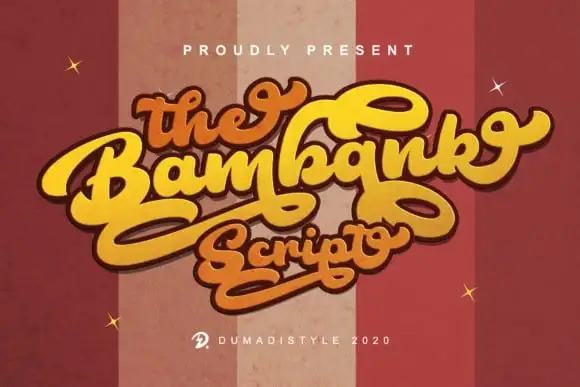
The Bambank Script Font – Download Grátis
A fonte ‘The Bambank Script Font’ é uma nova criação cuidadosamente meticulosa que adiciona linhas suaves e balanceadas a uma tipografia de script com personalidade. Suas letras fluídas são perfeitas para criar mensagens atrativas. Esta fonte foi projetada e compartilhada pelo designer DUMADI, caracterizada por um estilo vintage. O PUA está incluído, o que significa que você pode acessar todos os símbolos e swashes facilmente! Possui uma base variável, linhas suaves, góticos maravilhosos e alternativas estonteantes. Adore a sua versatilidade incrível e use-a para criar designs espectaculares. A ‘The Bambank Script Font’ é perfeita para quem deseja dar um toque sofisticado e autêntico à sua arte digital.